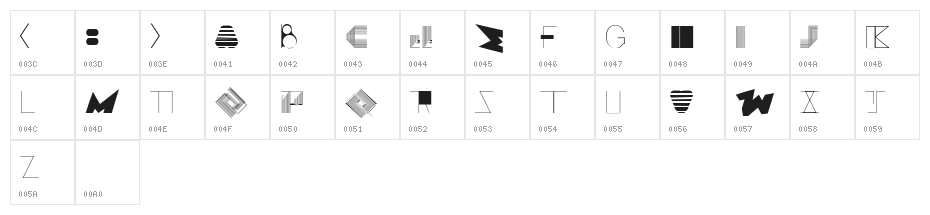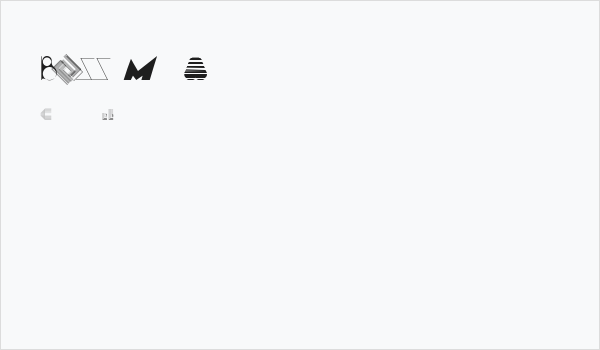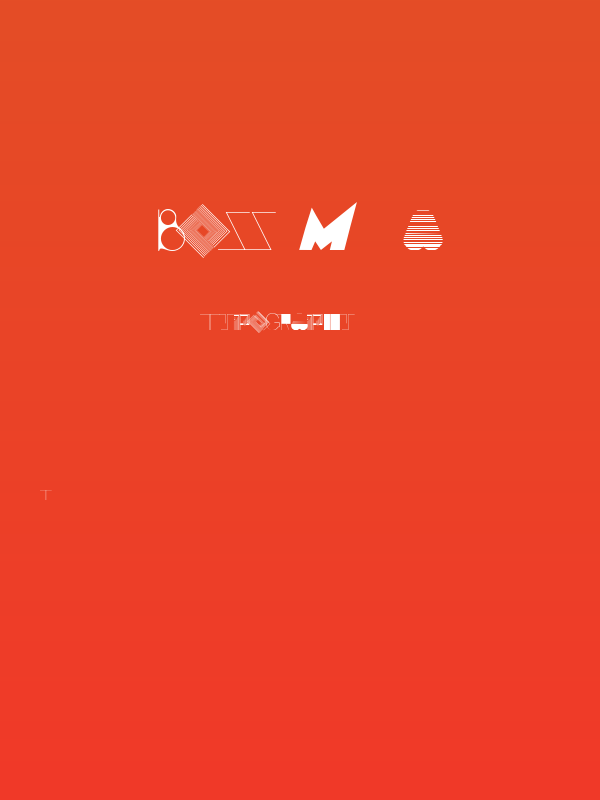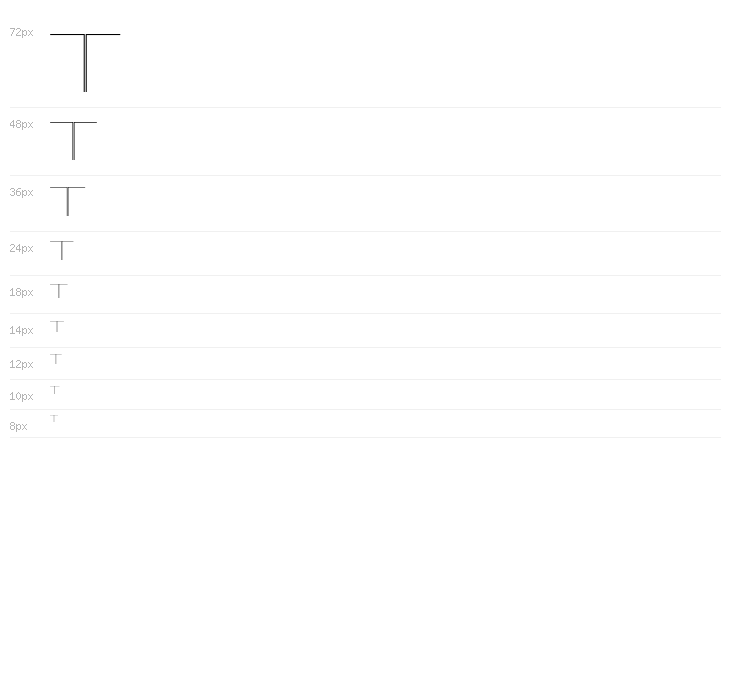
BOSS M A Font
✎ Decorative
| Anwendungsfall | Logos, Headlines, Posters |
| Vorgeschlagene Projekte | Ideal for branding, posters, album covers, and any project needing a modern, artistic touch. |